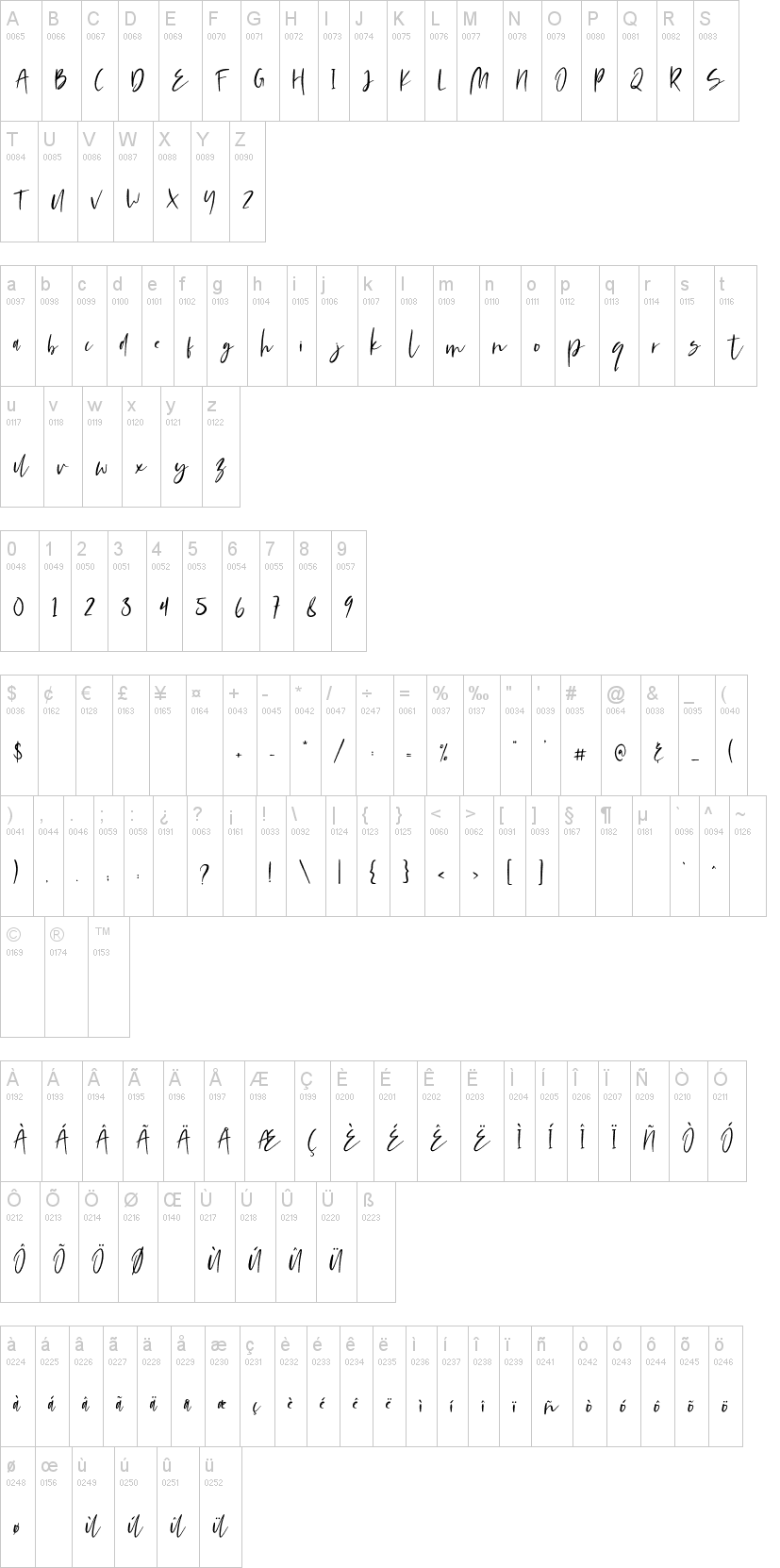
Mondela
Mondela 是一款新兴的时尚字体,它充分利用了现代设计技术,拥有简洁、清新、优雅的外观,适合用于时尚品牌、商业广告、网页设计等场景。Mondela 的字体结构清晰,具有良好的可读性,它的字母和数字的设计则更加的精细,具有更好的视觉效果。Mondela 字体还支持多种语言,可以满足不同国家和文化的需求。
Mondela是一款非常不错的手写艺术字体,具有很好的视觉感,适合于文化类的宣传设计、商业类品牌的广告和产品包装设计以及个性化文字排版等较多场景。